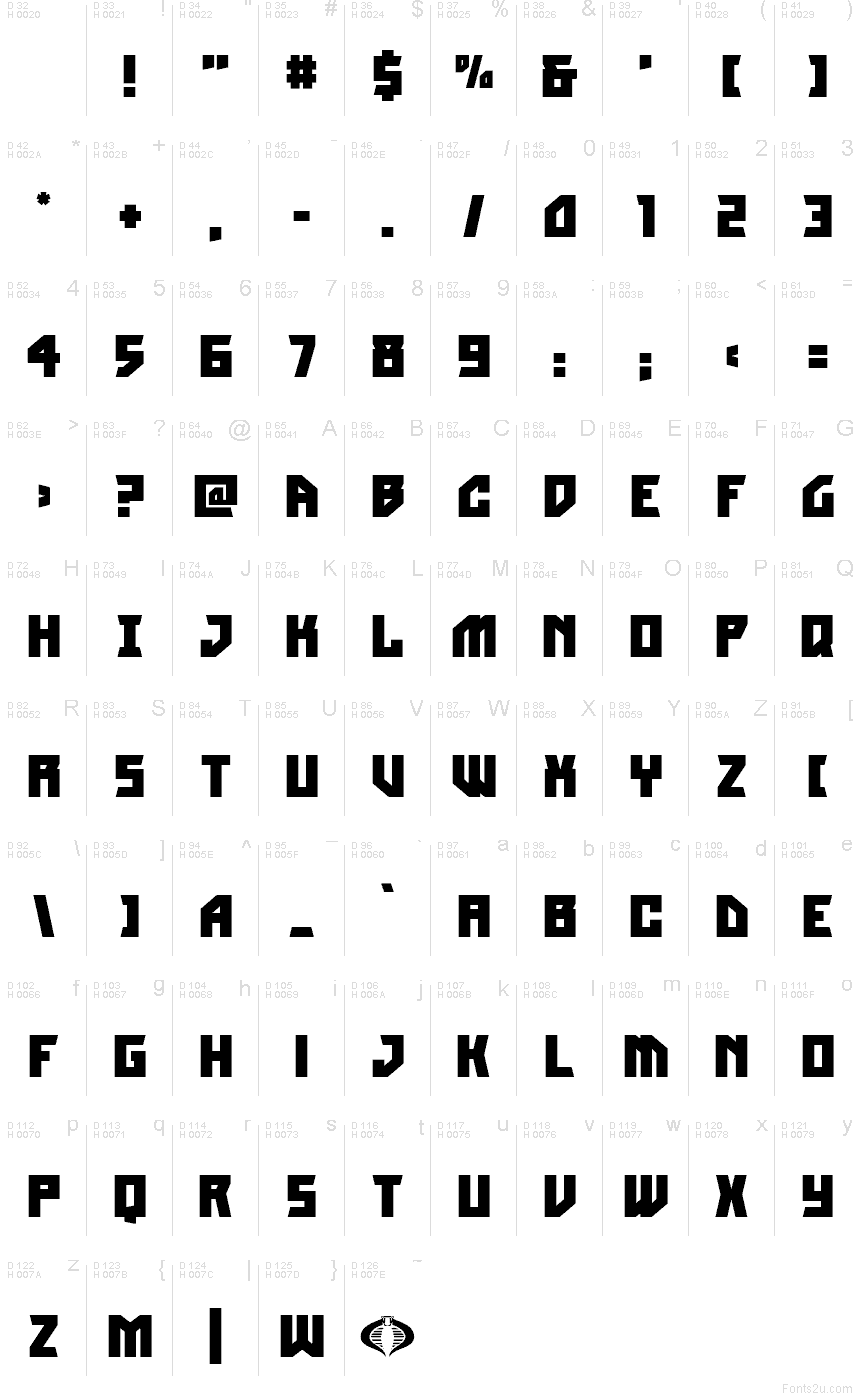
Omni-cobra Straight Expanded
Omni-cobra Straight Expanded par Iconian Fonts est une police d'affichage techno gratuite, caractérisée par des formes larges et carrées ainsi que des découpes internes tranchantes qui confèrent à chaque lettre un rythme rigide et sophistiqué. Les verticales droites et les jointures angulaires créent une sensation segmentée, presque mécanique, tandis que les espaces ouverts évitent aux formes de paraître trop massives.
Omni-cobra Straight Expanded est idéale pour les titres de science-fiction, les logos de jeux, le branding technologique, les en-têtes d'affiches, les écrans de démarrage d'applications et les accents sur les flyers ; ses cassures géométriques et son aspect élargi apportent une véritable identité numérique. Cette police gratuite convient également aux graphismes d'interface, au motion design et aux visuels promotionnels courts où une ligne structurée et futuriste est préférable à un tracé souple ou manuscrit.